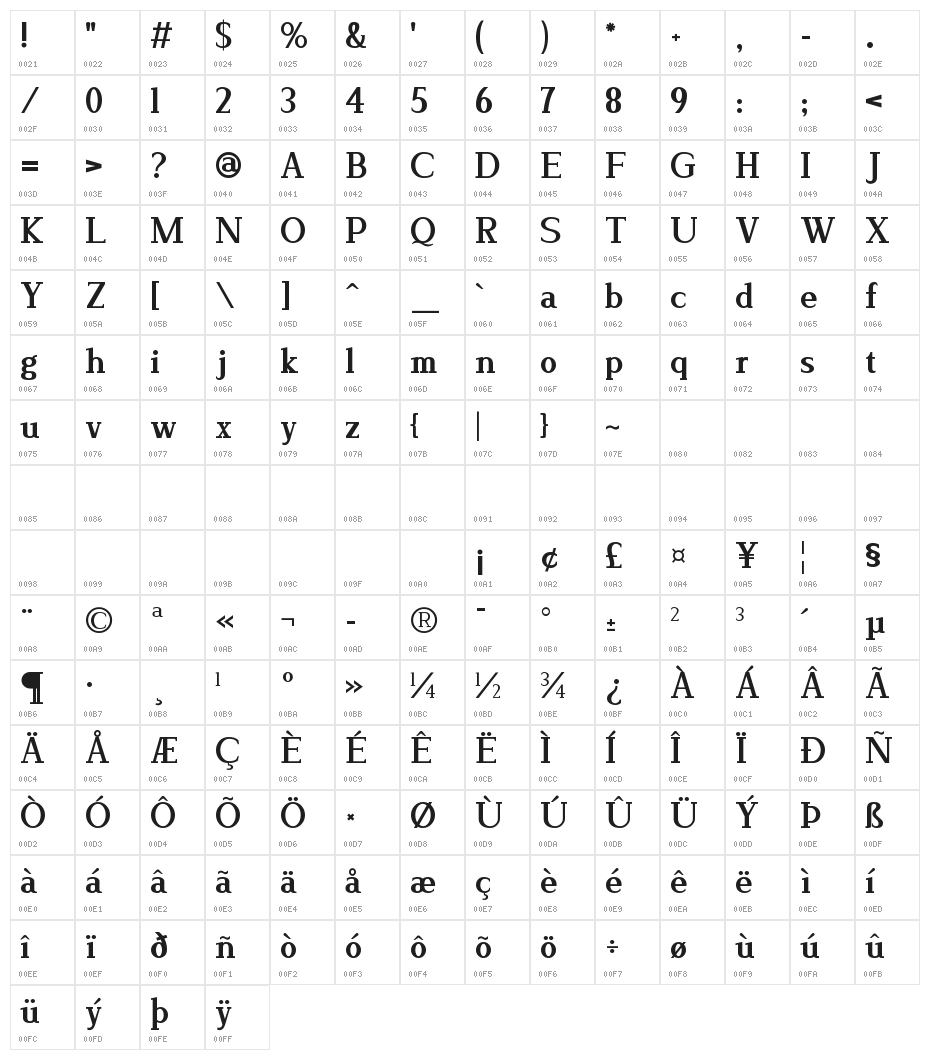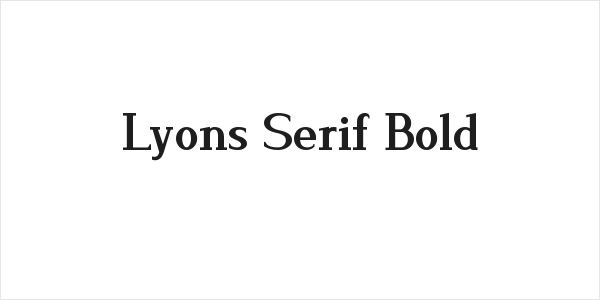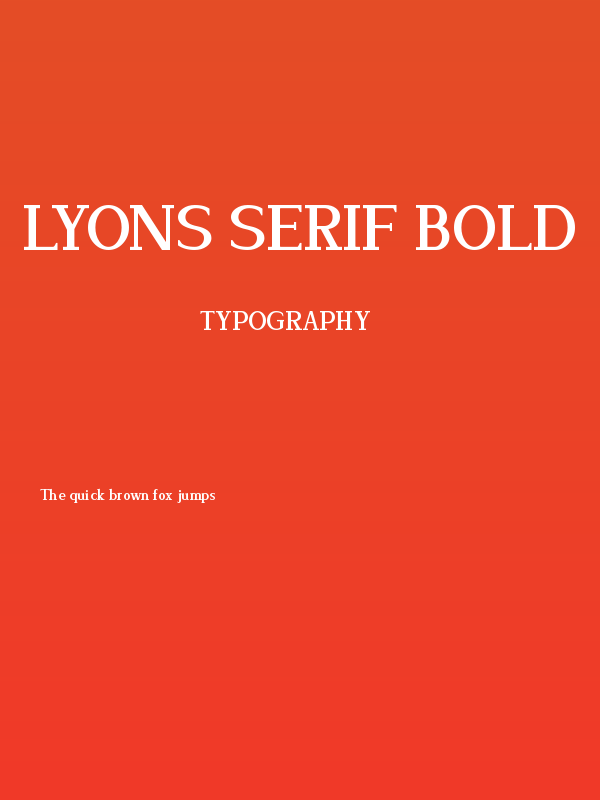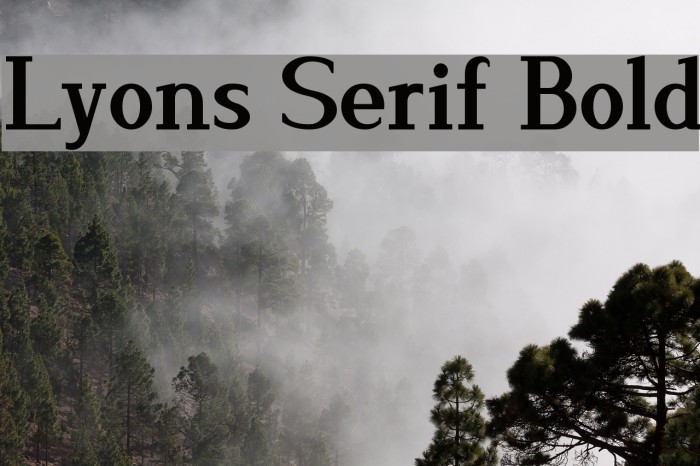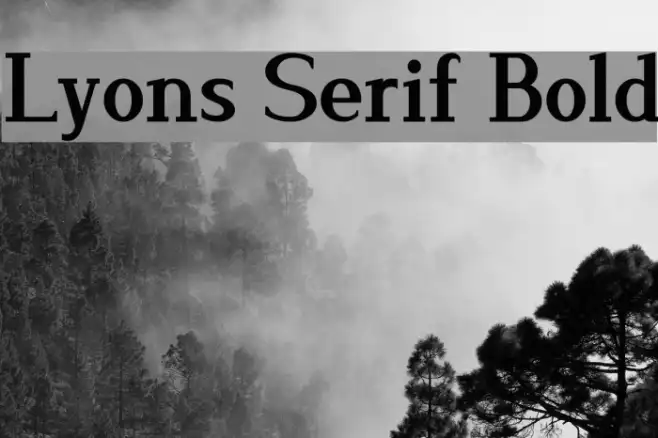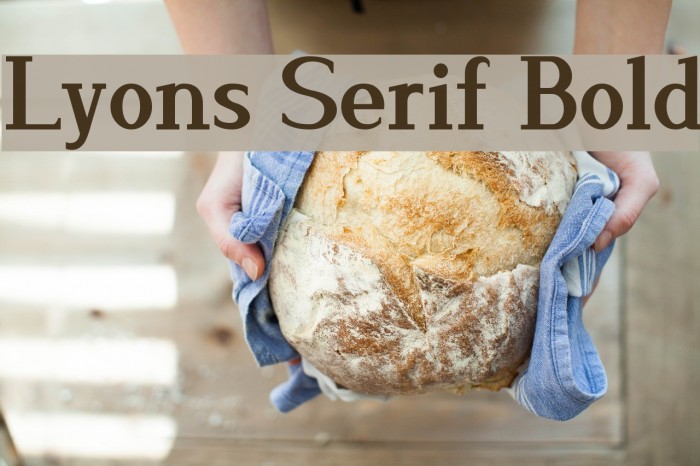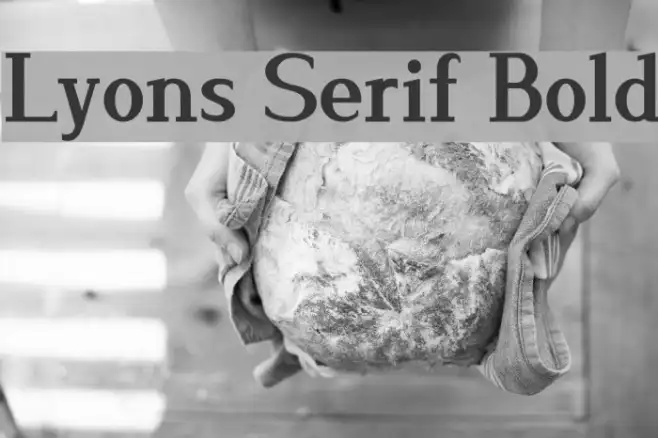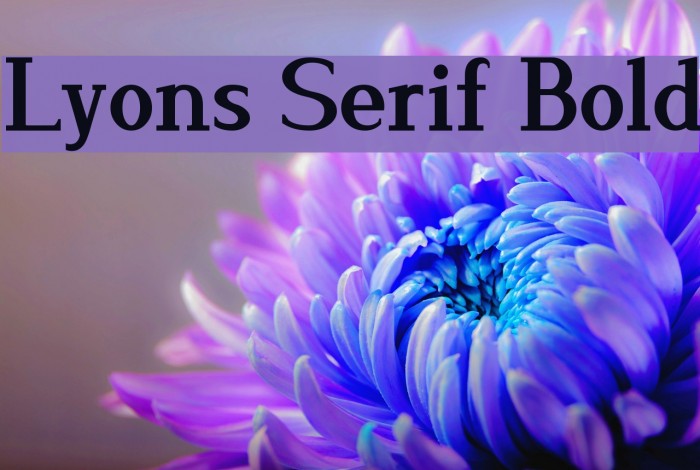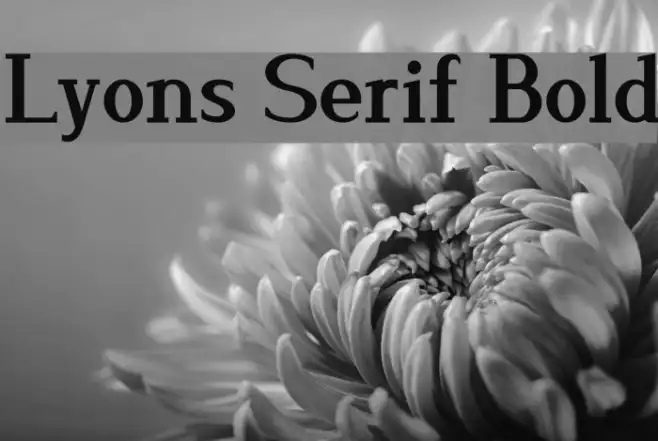
Lyons Serif Bold Font
| Style général | Classic |
| Projets proposés | Ideal for editorial design, book covers, formal invitations, and branding projects that require a traditional yet impactful look. |